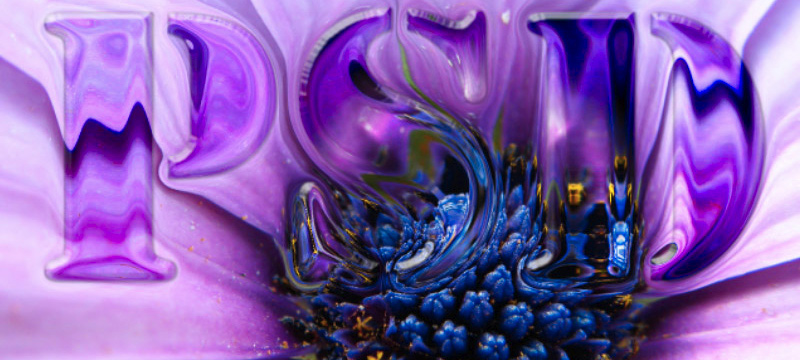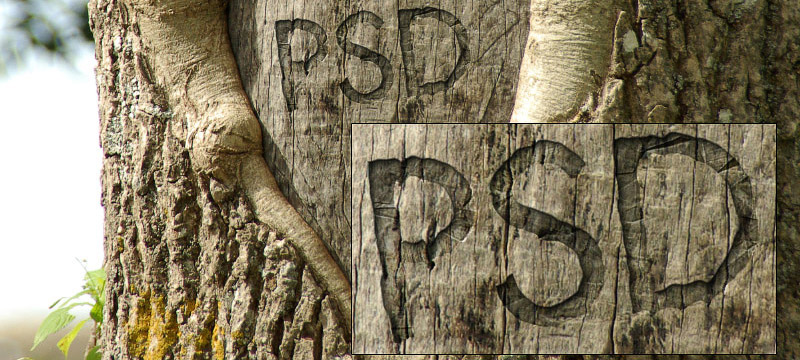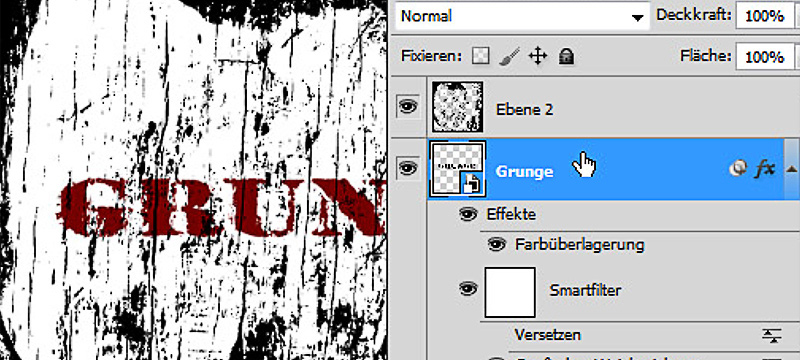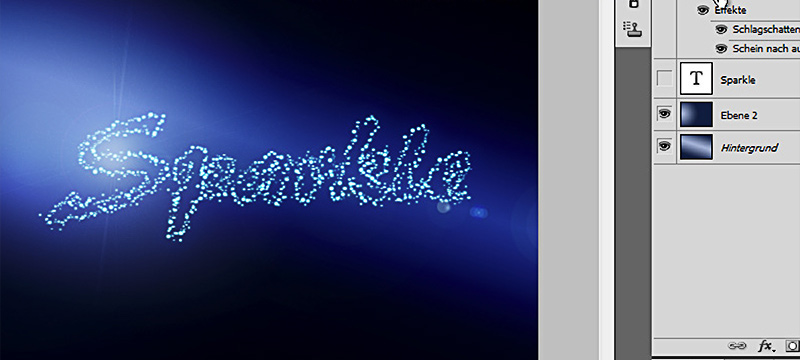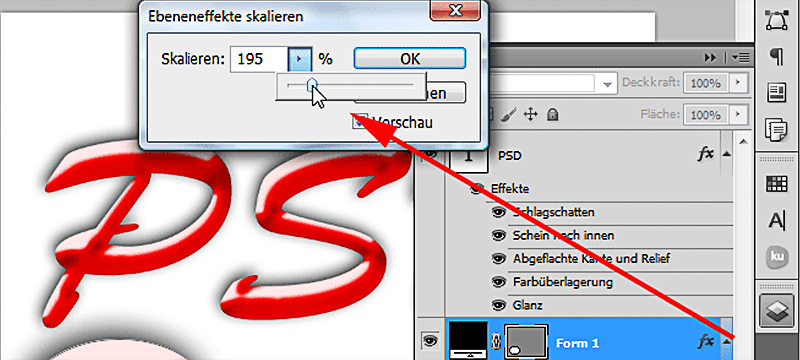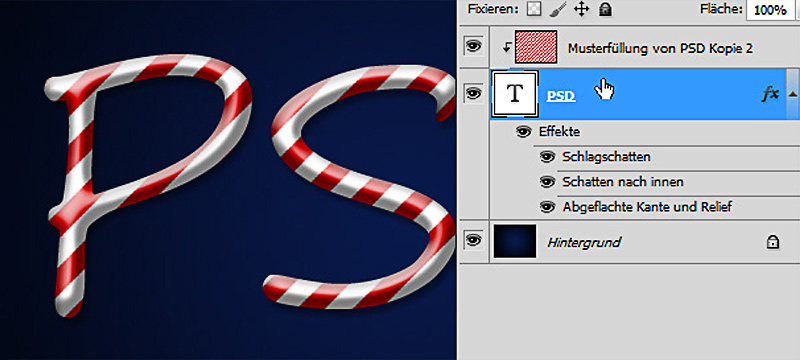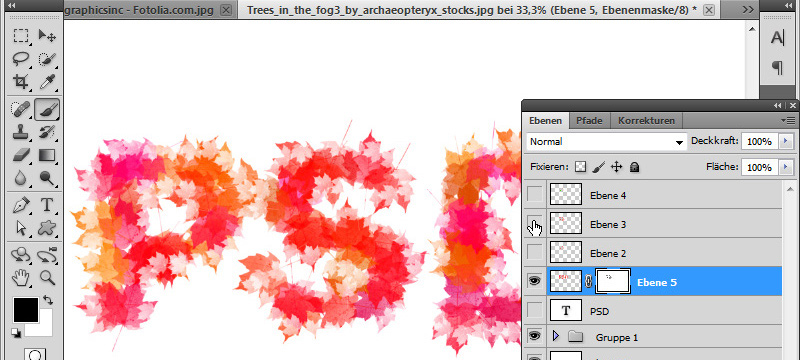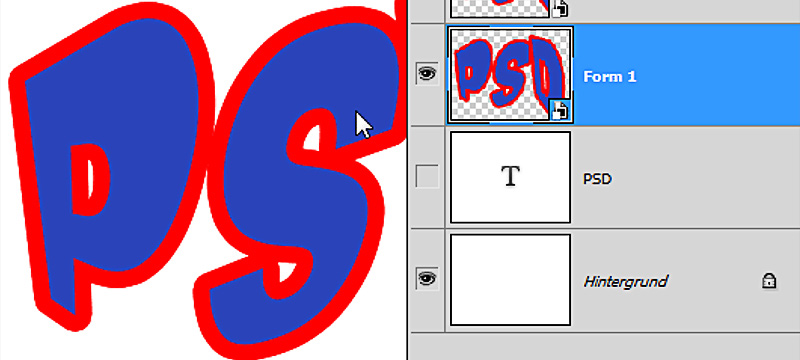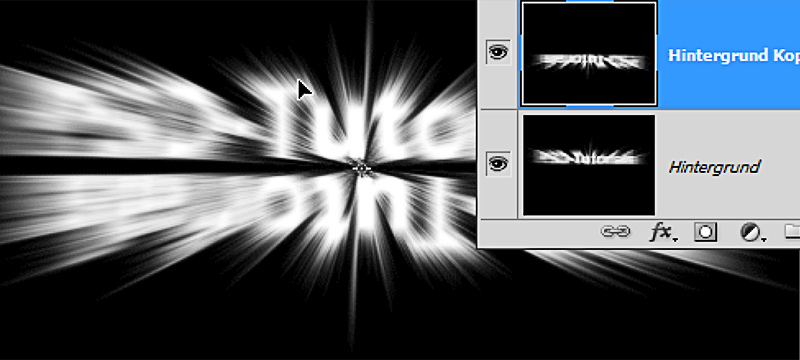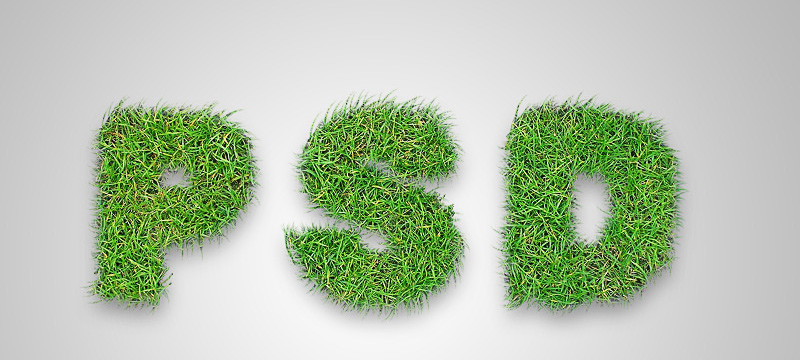
Tu manques de points accrocheurs créatifs ? Alors attire des regards curieux vers tes produits multimédias avec cette formation vidéo ! Le DVD de formation Photoshop Workshop - Effets pour la typographie, la mise en page et la photo - Vol. 1, avec 24 heures de vidéos, est ton chemin vers des résultats meilleurs, percutants et attrayants.
• Appliquer de manière ciblée des effets typographiques, de mise en page et de photo
Ça attire le regard, ça reste en mémoire ! Avec le savoir-faire des professionnels, tu réalises toi-même des effets saisissants pour tes dépliants, photos, sites web et bien d'autres supports !
Typo-effets (gratuit)
Cinq astuces rapides pour des effets typographiques classiques
Dans cette partie de la série Quicky, il y a cinq applications typo qui font partie de l'arsenal de base lors de travailler avec Photoshop.
Je vous explique:
• Mise en forme : placer du texte dans des formes
• Tracé de contours : laisser le texte s'écouler autour des objets
• Texte le long d'un chemin
• Regrouper du texte avec des images via un masque de découpe
• Remplissage de contours avec des motifs de pinceau le long de trajectoires de travail
Cinq astuces rapides pour des effets typographiques cool
Dans ce tutoriel, je vais montrer de petits "quickies typo" en créant très rapidement cinq effets de texte créatifs avec Photoshop.
Il s'agit notamment de :
1. Effet de contours rétro pour les titres,
2. Effet de contours effilochés pour les titres
3. Effet de réflexion simplifié en 3D
4. Effets de dégradé de réflexion dans les textes et formes
5. Texte incliné avec cadre
Créer un effet de verre pour la typographie et la mise en page
Dans cette formation vidéo, je veux montrer comment créer un effet de texte en verre transparent qui reflète l'arrière-plan brisé à l'intérieur et reste modifiable en termes de placement à tout moment. Je présenterai deux façons de créer le texte à effet de verre.
Effet de gravure sur bois pour la typographie et la mise en page
Dans ce tutoriel, je vais vous montrer un effet de gravure/sculpture dans lequel un texte est enfoncé dans le bois.
Effet grunge pour la typographie et la mise en page
Sous le terme Grunge, il existe de nombreuses façons de créer un style de typographie effiloché et déchiré. Dans ce tutoriel, je souhaite montrer plusieurs variations et approches pour les effets de Grunge sur les textes.
Créer du texte scintillant
Dans cette formation vidéo, je vous montrerai comment créer un texte composé uniquement de paillettes. De cette manière, nous créerons un chemin à partir d'un texte que nous remplirons avec différentes paramètres de pinceaux.
Créer du texte en plastique - Cinq variantes différentes
Dans cette formation vidéo, vous apprendrez comment créer différents effets de texte en plastique de différentes manières et approches.
Effet bonbon classique et illustratif
L'effet bonbon peut être très bien utilisé typographiquement pour les thèmes pour enfants, les sucreries, les boulangeries, etc. Je vais vous montrer dans ce tutoriel comment créer une typographie de bâton de sucre classique et illustrative.